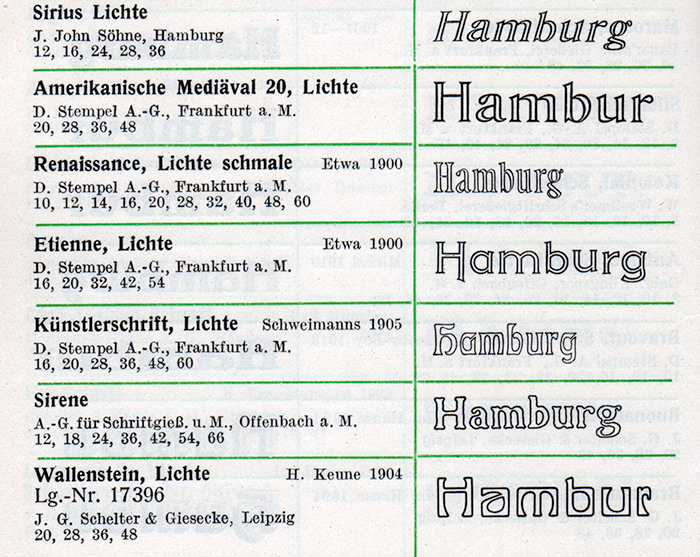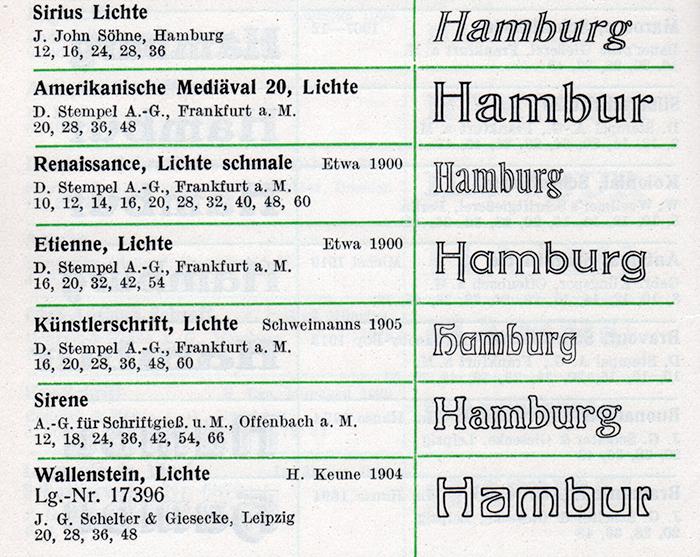
Lichte Schriften
Das Satztechnische Lexikon (1925) definiert licht als »alle zart, fein gezeichneten Schriften«, die sich damit insbesondere von den »kräftig, fett, schwarz gezeichneten Schriften unterscheiden«. Außerdem wird betont: »Konturschriften sind hier nicht einzureihen.«
Ungeachtet dieser Definition benutzten die Schrifthersteller im deutschsprachigen Raum die Bezeichnung »licht« insbesondere für solche Konturschriften, die heute, im Zuge der Globalisierung meist mit dem Zusatz »outline« bezeichnet werden. Wesentliches Merkmal ist aber, dass das Schriftbild nicht vollständig flächig gefüllt ist. Jede Art von innenliegender Linie rechtfertigt also die Bezeichnung licht.
Handbuch der Schriftarten, Seemann, 1926